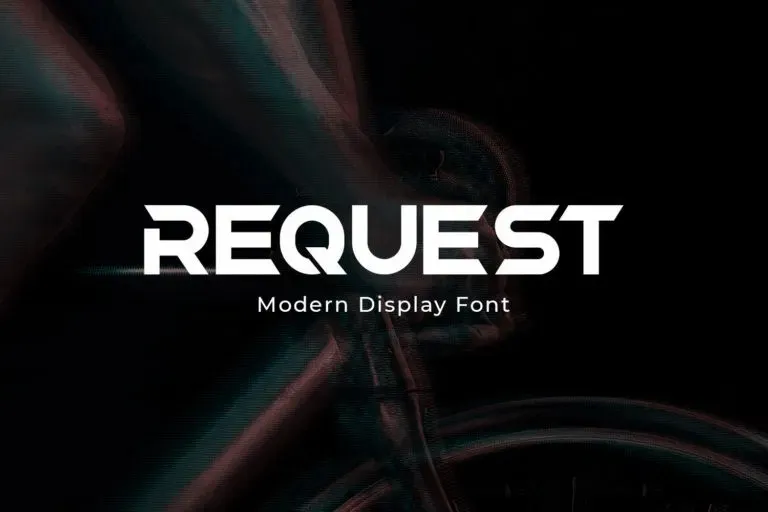
Esta é uma fonte display simples e acentuada que impressiona com sua elegância e precisão. Foi criada pelo designer Din Studio, famoso por suas formas geométricas abstratas. Esta fonte não apenas complementará sua paleta de fontes existente, mas também a enriquecerá com uma qualidade única e moderna. A dinâmica e o brilho que ela traz aos seus trabalhos irão destacar a sofisticação e a criatividade em todos os ambientes onde você a usar. Seja ele um projeto de logotipo, um site elegante ou até mesmo material gráfico para redes sociais, esta fonte será uma escolha ótima que ajudará a torná-lo ainda mais chamativo e inovador. Com sua capacidade impressionante de se adequar em diversos cenários, a fonte Display do Din Studio é perfeita para quem busca trazer um toque único e moderno aos seus projetos. Seja você um designer profissional ou um aficionado por design, esta fonte pode transformá-lo no centro das atenções e na vanguarda da moda gráfica atual.